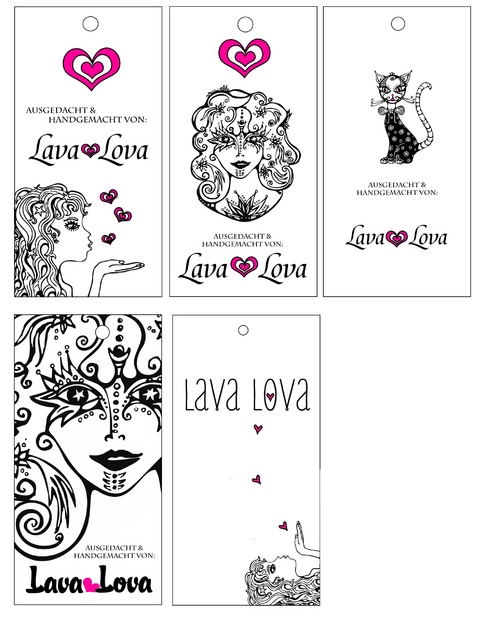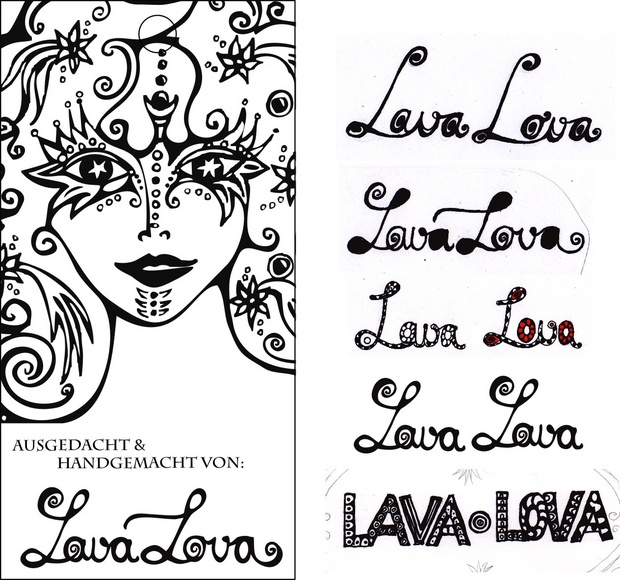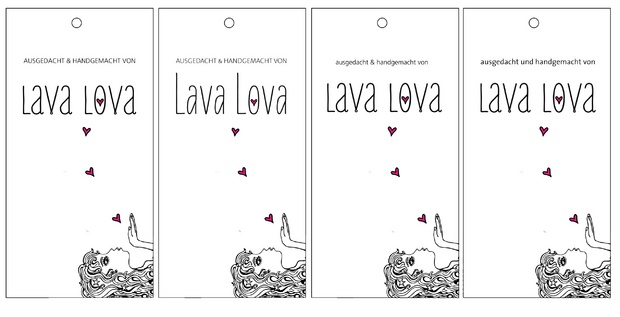
Hangtags-Siebdruck-Logo-Schrift
Bitte um konstruktive Kritik - Hangtags-Siebdruck
Hallo liebe Schriftliebhaber,
gleich zu Anfang, Schriftgestaltung ist nicht mein Gebiet, Hut ab vor jedem, der das Auge für gutes Typodesign hat.
Ich habs leider nicht, fehlt Kenntnis, Erfahrung und auch das sprichwörtliche Auge.
Jetzt muss ich aber doch auf diesem Terrain arbeiten, zum Glück gehts nur um eigene Sachen. Ich möchte für meine kleine Siebdruckkollektion Hangtags (Anhänger) gestalten und da kommt das eine zum anderen und am Ende hat man ein komplettes Corporate Design zu kreiren.
Der Anfang ist gemacht, ich hab entworfen und verworfen, das Ergebnis möchte ich eurem geschulten Auge zeigen.
Wohlgemerkt es sind Skizzen, also bitte nicht an Kleinigkeiten aufhängen, mir gehts in erster Linie um eine zu mir und meinen Sachen passende Schrift und die wiederum zur Logoschrift passende Schrifttype.
Da das ganze auch mit den Drucksachen (Taschen,Kindergartenbeutel,T-shirts,Kissen) harmonieren soll, habe ich noch ein paar Beispielbilder hochgeladen.
Danke für Deine Antwort.
An Langnese hab ich gar nicht gedacht, siehste mal wie gut mein Werbefilter schon funktioniert. Muss ich umstellen, danke für den Tip.
Ich hab in Richtung Handschriften schon etwas probiert, war mir irgendwann zu viel Schwung in der Sache.
Bei deiner Arbeit sieht das schön aus, da ist das Foto ein guter Kontrast.
Bei mir sind es dann einfach zu viele Kurven.
Liebe Anne,
spontan drauf geschaut gefällt mir das rechte untere Hangtag am besten: Die Schrift ist schön schlicht, dabei hat sie aber ganz viel Charme und passt Du den Zeichnungen, die Du verwendet hast. Auch die Komposition des Hangtags ist schön spannungsreich. Die anderen Schriften sind für mein Empfinden schon zu verbraucht, man hat diese oder ähnlich Schriften schon zu oft gesehen und häufig wurden sie leider auch für billige Produkte eingesetzt, ich würde sie daher nicht nehmen. Die Schrift auf dem von mir präferierten Hangtag sagt: »handgemacht und das mit Liebe zum Detail«. Ich würde deswegen ganz klar gestalterisch in diese Richtung gehen und vielleicht auch noch mal ähnlich anmutende Schriften ausprobieren, falls Du Dir in der Schriftenfrage noch nicht sicher bist. Schau doch mal diesen Link an, die Schriften von Ulrike Wilhelm könnten interessant sein für Dich. :-)
Bei deiner Arbeit sieht das schön aus, da ist das Foto ein guter Kontrast.
Das ist natürlich nicht meine Arbeit... Aber ich wohn da um die Ecke und finde das ganz hübsch.
Kleine Anmerkung: Was Du da gerade versuchst ganz schnell zu machen, braucht auch bei sehr talentierten Leuten gerne mal Wochen... Womit ich vor allem meine, dass man Dinge auch mit Abstand betrachten muss.
Ich würd jetzt nicht die Schrift in einen dekrativ-verschnörkelten Wettbewerb mit den Illustrationen schicken sondern einen eher schlichten Kontrast dazu wählen.
An LiebeFonts mußte ich auch sofort denken! :-D
Sowohl die LiebeErika, als auch die LiebeDoni passen meiner Meinung nach gut zu Deinen schönen Zeichnungen.
Die Schrift von „Ausgedacht und …“ würde ich nicht verwenden; ich bringe sie nicht mit hochwertiger Handarbeit, sondern mit Harry Potter und Altertum in Verbindung. (Welche Schrift ist das? Sie wirkt so vertraut, aber ich komme nicht drauf.)
... spontan drauf geschaut gefällt mir das rechte untere Hangtag am besten ...
geht mir genauso.
(Welche Schrift ist das? Sie wirkt so vertraut, aber ich komme nicht drauf.)
Galliard? Kann das sein?
vielen Dank für eure zahlreichen Antworten.
Das letzte ist ja auch deshalb das letzte, weil ich irgendwann die Faxen dicke hatte von den vielen Kurven und meinen Computerschriften und im Netz auf Suche gegangen bin. Über die Liebe Fonts bin ich dank eurer Seite auch schon gestolpert, die werden in Zukunft sicher ordentlich genutzt im deutschsprachigen Raum. Ich finde sie sehr schön und werde sie mal probieren.
Desweiteren bin ich mir auch bewusst,dass ein gutes Design Zeit und auch ein Liegenlassen und wieder draufschauen benötigt.
Die befragte Schrift heisst bei mir Charlesworth.
Kann ich denn mein - ausgedacht und handgemacht - auch in derselben Schrift wie das Logo schreiben, beim letzten Entwurf hab ich noch nix stehen?
Vielen Dank für die Richtung und vor allem den Hinweis, dass meine Schriften schon so verbraucht sind
Liebe Anne,
probier es doch einfach mal aus! Setzt den Text mal einheitlich aus Deiner Logoschrift und schau, was dann optisch passiert. Ich könnte mir allerdings vorstellen, dass das »ausgedacht und handgemacht« einen sehr schönen Kontrast zum handschriftlichen Logo bilden würde, wenn Du es in einer ganz reduzierten serifenlosen Schrift setzt. Ich würde da mal die TheSans oder auch die Frutiger ausprobieren in einem leichten Schriftschnitt. Falls Du die Schriften nicht hast sag Bescheid – ich kann sie Dir gerne setzen und in Pfade konvertiert schicken – einfach per PN Bescheid sagen und mir Deine E-Mail-Adresse geben. :-)
Liebe Kathrin,
herzlichen Dank für die Vorschläge, ich habe beide Schriften gefunden und ausprobiert.
Was meinst du?
Die LiebeErika finde ich auch toll, wenn denn das a nicht wäre. Aber vielleicht gewöhne ich mich dran.
Wahrscheinlich ist das Ganze jetzt zu zart geworden, um es im Siebdruck zu setzten. Das ist ein bisschen schade.
Ich werde ein paar Ausdrucke machen und an die Drucksachen hängen - zur Probe. Dann lege ich mir meine neue Identität unters Kopfkissen und schlaf ein paar Nächte drüber. Hoffe, das gibt gute Träume.....